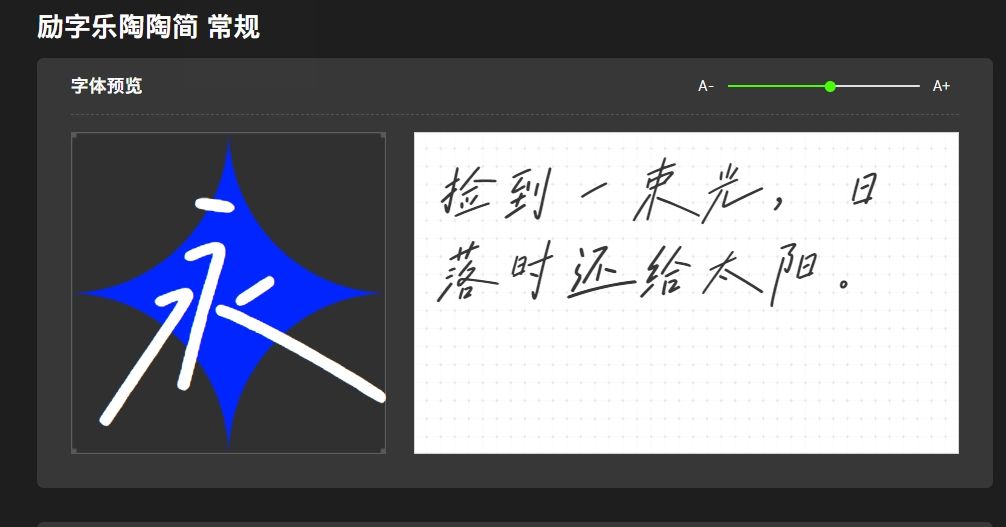
励字乐陶陶简,春季文艺字体下载!
春天,万物复苏,生机勃发,是文艺创作的灵感源泉。在这个充满诗意的季节里,文字也需要一款与之匹配的字体来增添文艺气息。接下来,让我们一同探索几款适合春季文艺创作的字体推荐,为你的文字披上一层浪漫与柔情的轻纱。
励字乐陶陶简 常规,字体在创作时均采用了简洁直爽的单线笔画整体字形偏窄并向右上方倾斜,增加了整体的统一度和韵律感。字体结构布局左收右放,左紧右松的特点,使其在应用到整体排版时,增加了段落的空间感和通透感春风拂面,轻柔而温暖。这款字体以春风为灵感,线条流畅而自然,给人一种舒适与愉悦的感觉。适合用于旅游宣传、自然风景类文章的排版,让读者在文字的引导下感受春天的美好与宁静。
春天是文艺创作的最佳时节,选择一款与之匹配的字体能让你的文字更加生动、引人入胜。